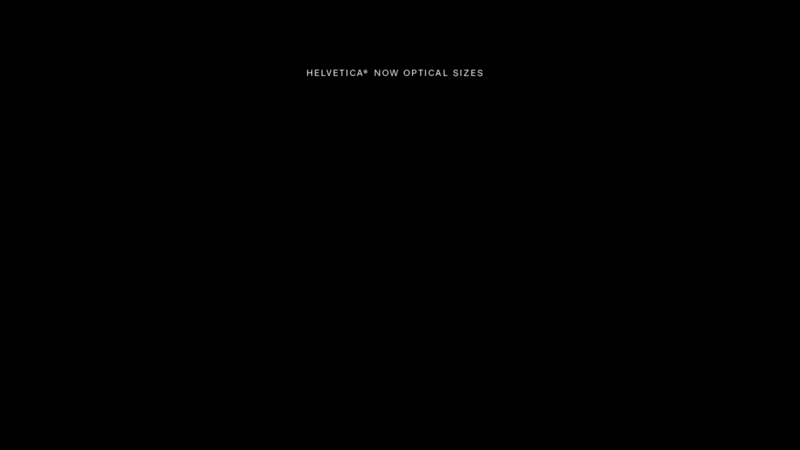
¿Qué es el tamaño óptico y cómo ayuda a tu marca?
Helvetica® Now, el último lanzamiento de Monotype Studio, incluye tres tamaños ópticos (microtexto, texto y pantalla) diseñados para optimizar la legibilidad en una amplia variedad de aplicaciones. Los diseñadores y diseñadoras de tipografías conocen bien el concepto de los tamaños ópticos. Sin embargo, este término puede no ser tan conocido entre especialistas de marca, marketing y diseño gráfico. Veamos en qué consiste y cómo ayuda a las marcas a transmitir mensajes claros y eficaces a su clientela.
“
Desde texto publicitario de gran tamaño en pantalla hasta microtipos hiperlegibles en el diseño de información multinivel. ”
Diseñar en función del contexto
El desarrollo de tamaños ópticos es la práctica de diseñar versiones diferentes de una fuente teniendo en cuenta cómo y dónde se utilizará. Por ejemplo, la fuente Helvetica se percibe de forma diferente cuando se utiliza en un valla publicitaria en la calle que cuando se emplea en la pantalla de un teléfono o en el cuerpo de un texto. Los tamaños ópticos se desarrollan para adaptar las fuentes a los distintos contextos, teniendo en cuenta que los matices en la forma de los caracteres, el espaciado y el kerning influyen tanto en la legibilidad como en el estilo. Diseñar la fuente en un tamaño óptimo y «cruzar los dedos» para que funcione bien (o medianamente bien) en todos los tamaños es una práctica habitual. Sin embargo, los diseños de tipos en un solo tamaño (o «single master») no tienen en cuenta todos los matices.
Helvetica Now optical sizes
Sobre la restauración de Walbaum, una familia de tipos con remates clásicos, para adaptarla a la era digital, el director de tipos de Monotype, Charles Nix, explicó lo siguiente: «Imaginemos que todos nos ponemos de acuerdo en que los niños y niñas de 10 años tienen la forma humana óptima y que, en lugar de tener bebés, “encogiéramos” a esos niños de 10 años hasta el tamaño de un bebé y, después, los “ampliáramos” hasta el tamaño de un adulto o adulta. Al igual que los bebés no son niños y niñas de 10 años en miniatura, los tipos de 5 puntos no son tipos de 12 puntos reducidos».
Antes de la llegada de los ordenadores, los diseñadores y diseñadoras de tipografías cambiaban el diseño para cada uno de los tamaños de los tipos de letras con el fin de preservar el estilo y la legibilidad en toda la gama de usos. Los tamaños más pequeños requerían un mayor espaciado entre caracteres y mayores aperturas en las formas de las letras para mejorar la legibilidad. Por el contrario, a los tamaños más grandes les sentaban bien un mayor contraste de los trazos y detalles más elegantes. Sin embargo, cuando los tipos se digitalizaron con la llegada de los ordenadores y los diseños de un único tamaño, diseñar tipos de «talla única» se convirtió en lo habitual.
¿Y qué es lo normal?
Ahora que ya sabemos que la talla única no es un enfoque viable, las fundiciones de tipos están diseñando y restaurando digitalmente las fuentes con optimizaciones de tamaño específicas con el fin de preservar la integridad del diseño.
Aunque lo primero es abordar elementos clave del diseño, para Charles Nix, desarrollar tamaños ópticos es una combinación de ciencia y arte a partes iguales.
«Se requiere una sensibilidad artística hacia las formas y los espacios intermedios, pero las mejoras reales se consiguen a través de la observación, el desarrollo de hipótesis y la experimentación. Es un proceso de estudio, prueba-error y perfeccionamiento; el proceso de diseño iterativo habitual», explica Charles Nix.
De hecho, el director de tipos de Monotype siempre empieza con una pregunta. «“¿Y qué es lo normal?” es la pregunta que me formulo cuando diseño una fuente con tamaños ópticos. Parece una crisis existencial, pero los diseños para tamaños muy pequeños deben transmitir la misma sensación que un texto de tamaño normal. Del mismo modo, en los diseños más grandes, la fuente normal debe perfeccionarse, ya que los textos se verán muy de cerca. ¿Y qué es lo normal? Es la esencia de la intención del diseño: sus valores fundamentales».
“ «¿Y qué es lo normal?», se pregunta Charles Nix. «Es la esencia de la intención del diseño: sus valores fundamentales». ”
Al redefinir Helvetica, una familia creada hace más de 60 años, el equipo de Monotype se mantuvo fiel a la intención original: una fuente que transmitiese claridad, sencillez y neutralidad. El resultado, Helvetica Now, es la Helvetica mejorada para responder a las necesidades actuales. Compuesta por 48 fuentes en tres tamaños ópticos (pantallas, texto y microtexto), la familia destaca en entornos de alta y baja resolución y, según Nix, «funciona a la perfección en toda la gama de aplicaciones de diseño, desde texto publicitario de gran tamaño en pantalla hasta microtipos hiperlegibles en el diseño de información multinivel».
Los tamaños de pantalla más grandes, pensados para tamaños de 14 puntos en adelante, están cuidadosamente diseñados para reflejar la sutileza de la Helvetica, pero también cuentan con el espaciado suficiente para encajar bien en todo tipo de cabeceras. Los tamaños de texto estándar, para tamaños de 8 a 12 puntos, se han diseñado y espaciado para cumplir con los requisitos de legibilidad propios de los textos extensos. Para facilitar la lectura, los trazos son robustos; el contraste, reducido; y el espaciado, relajado. La gama de grosores proporciona una paleta amplia para entornos con mucha información.
Los tamaños de microtexto, para tamaños de 3 a 7 puntos, son perfectos para composiciones tipográficas muy pequeñas y para entornos de baja resolución. Las formas se han simplificado y exagerado para mantener la impresión de la Helvetica, mientras que el espaciado es intencionadamente holgado, algo esencial para lograr un microtexto hiperlegible.
El estilo y la legibilidad son aspectos fundamentales en todo tipo de usos, desde carteles hasta aplicaciones móviles. Los mensajes de marca tienen que funcionar a la perfección en un entorno hipercompetitivo. Y es que cualquier problema de legibilidad o falta de coherencia en el estilo va en contra de la marca. Los tamaños ópticos no solo funcionan mejor, sino que son más atractivos.